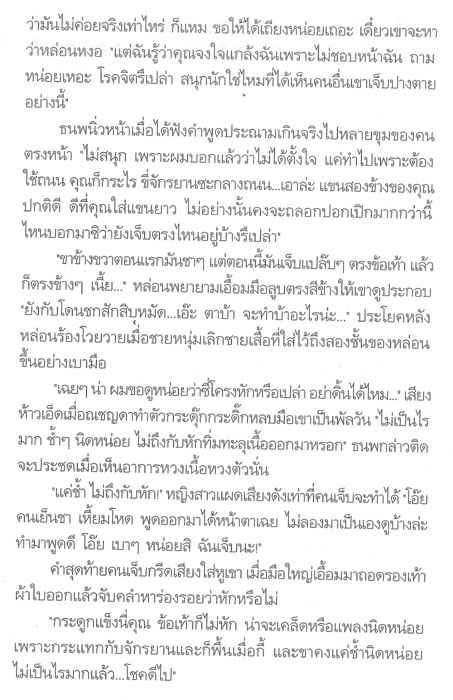
ฟอนต์นี้ชื่ออะไรครับ
ฟอนต์นี้ชื่อฟอนต์อะไรครับ เห็นน่าใช้ดี ทำให้หนังสือดูน่าอ่านขึ้น
จากเพชรพระอุมา
ผมว่ามันคล้ายๆ JS Arisa กับ TF Chiangsaen นะครับ
แต่คิดว่าหนังสือคงใช้เครื่องแม็ค เลยไม่รู้ว่าในแม็คเรียกฟอนต์นี้ว่าฟอนต์อะไร
ส่วนจากอีกเล่ม
ผมว่าคล้ายๆ JS Jindara ครับ
แต่ส่วนตัวผมชอบใช้ Dillennia UPC ที่ติดมากับเวิร์ด
แล้วขยายฟอนต์เอาสัก 113% ก็ออกมาคล้ายๆ
พิมพ์ text สวยเหมือนกันครับ